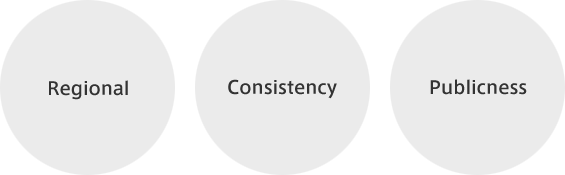
都市フォント構想は、都市が独自に持っている個性や魅力をフォントのデザインに取り入れることで、都市らしさを具現化するための構想です。都市オリジナルのフォントをあらゆる媒体に統一的に使用することで、都市アイデンティティの形成を助け、市民の一体感を醸成し、都市景観に貢献するツールとなります。
欧米を中心に都市間で生き残り競争が激化しており、都市ブランディングの重要性が高まっています。ローマやソウルなどの都市では、都市の案内サイン、ウェブサイト、ポスター、リーフレット等の視覚的コミュニケーションにおいて、フォルムの美しさや機能性だけでなく、その都市らしさを反映させたフォントを新たにデザインし、活用することで、その都市のブランディングを効果的に進めています。
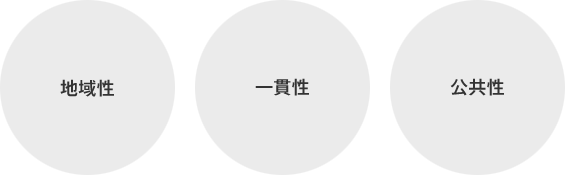
- 方言との結びつきが感じられる書体(訛り・アクセント・イントネーション etc.)
- 地方の味を彷彿とさせる書体(濃い・淡い・まろやか・芳醇 etc.)
- 土地の人の気質が感じられる書体(あっさり・穏やか・大人しい etc.)
- 風土や気候を表現した書体(寒い・曇りがち・雪国・荒波・山並・川面 etc.)
- 地方独自のモニュメントや動植物をモチーフにした書体(遺跡・草花・昆虫・鳥獣 etc.)
- 自分の街に誇りを持てる
- 都市景観との調和
- 市民が納得する制作プロセス
- 利便性と公益性の高い提供方法とその運用